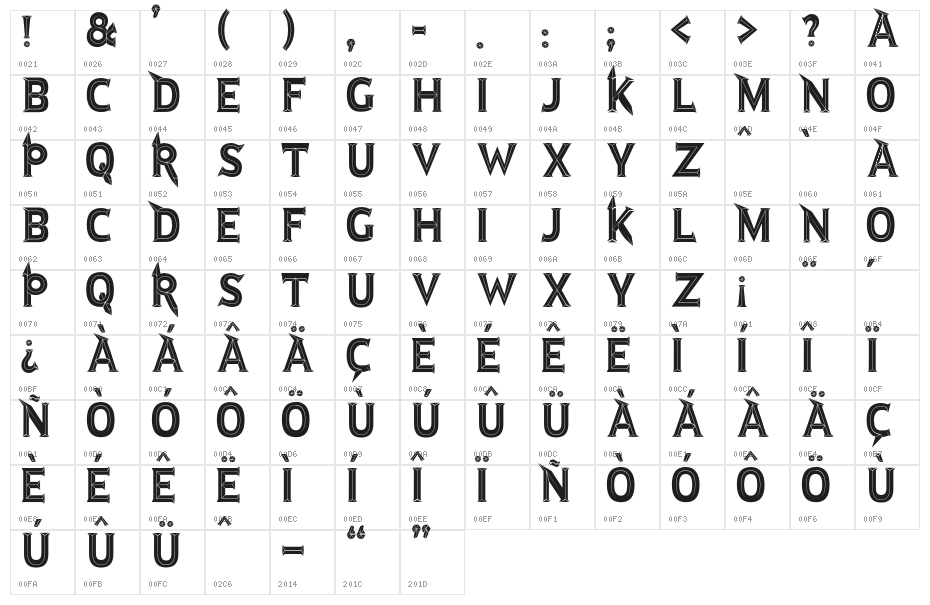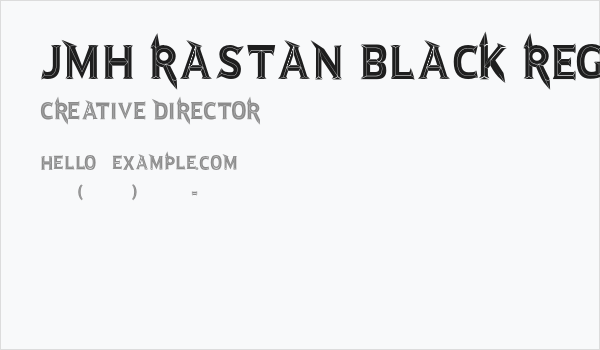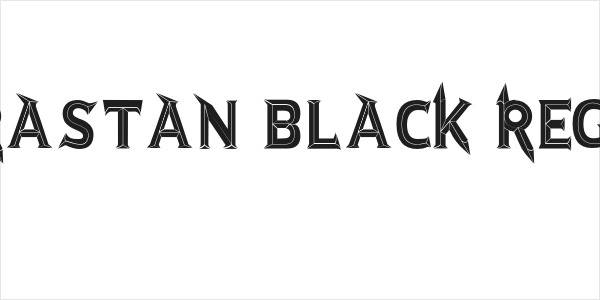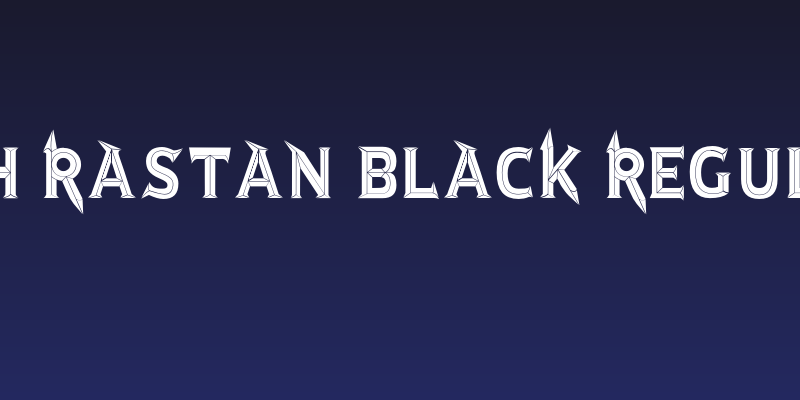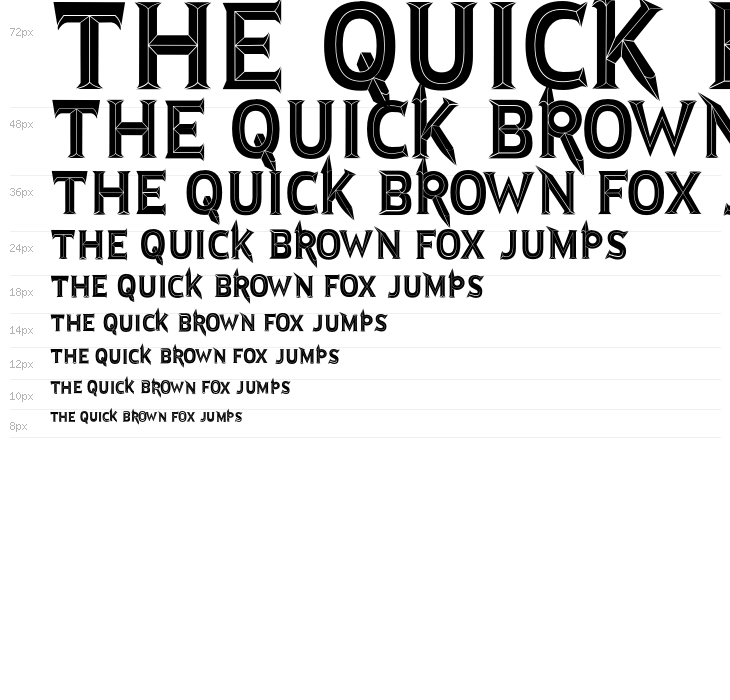
JMH Rastan Black Regular Font
✎ Art Deco
| Категория | Art Deco |
| Общий стиль | Vintage, Modern |
| Рекомендуемые проекты | Ideal for video game titles, movie posters, branding for edgy products, or any project requiring a strong, eye-catching typeface. |